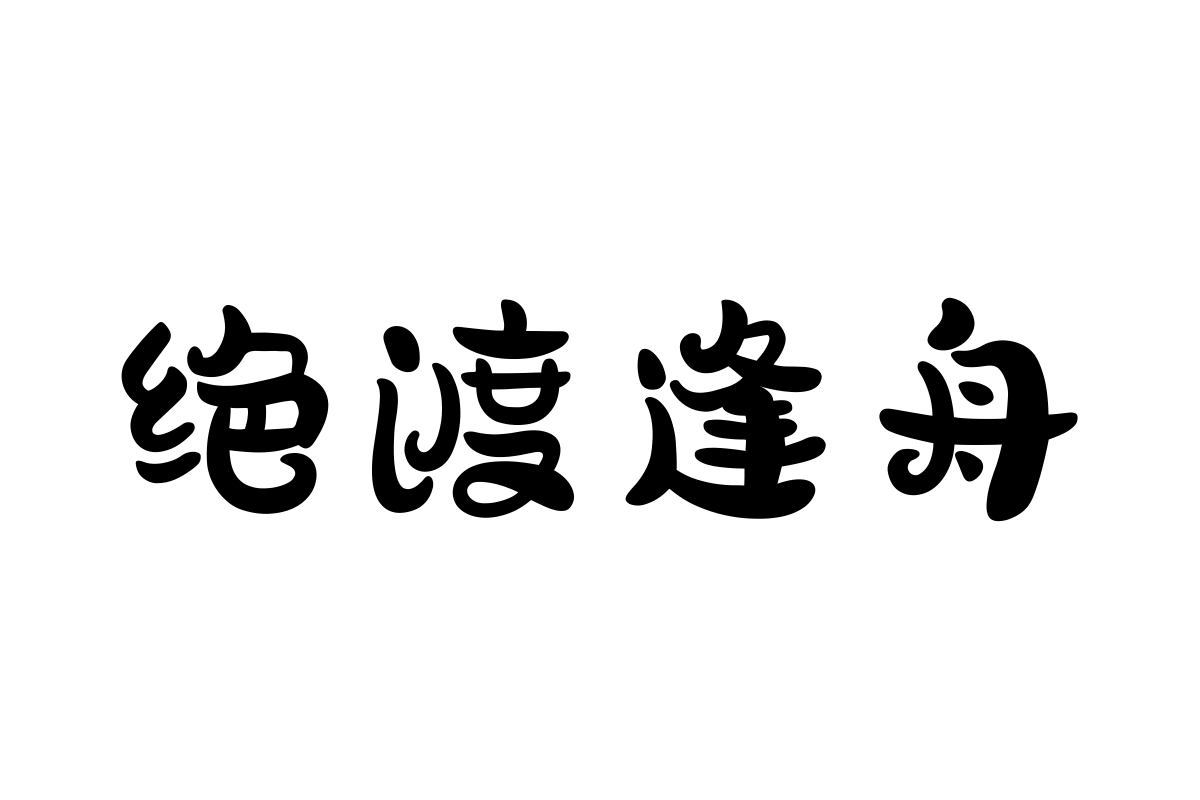
汉仪尚巍魔法体精修版是一款由汉仪字库推出的中文字体,具有以下特点:
1. 字形美观:该字体的字形设计独特,线条流畅,笔画清晰,整体给人一种优雅、庄重的感觉。
2. 风格多样:该字体的风格多样,可以用于各种场合,如标题、正文、广告等,具有很强的通用性。
3. 易读性强:该字体的字形结构简洁明了,笔画粗细适中,使得阅读起来非常舒适,不易产生视觉疲劳。
总之,汉仪尚巍魔法体精修版是一款实用性强、风格多样、易读性好、兼容性好的中文字体,适用于各类设计需求。